艺术字体是什么呢?为什么有众多人会选择设计字体呢,在线艺术字体逐渐发光发热,庄重醒目,一些字体粗壮有力,可以对品牌或个人起到直接性的宣传作用,一些字体结构匀称,代表了不同人的不同性格,那么在线艺术字体设计要知道哪几点呢?如何让该种艺术变得更加立体?
艺术字比较重要,在线艺术字体是很多人名和logo的主打字体,现在很多的一线品牌或者是知名品牌,它们对艺术字是非常重视的,在进行品牌更新或者是logo升级的时候,都非常突出艺术字的地位和重要性,比如我们经常看到的可口可乐,或者更新后谷歌的英文艺术字,它们都是强调了艺术字的重要性。可口可乐是中文艺术字,而谷歌的英文艺术字也非常细腻、非常好看。
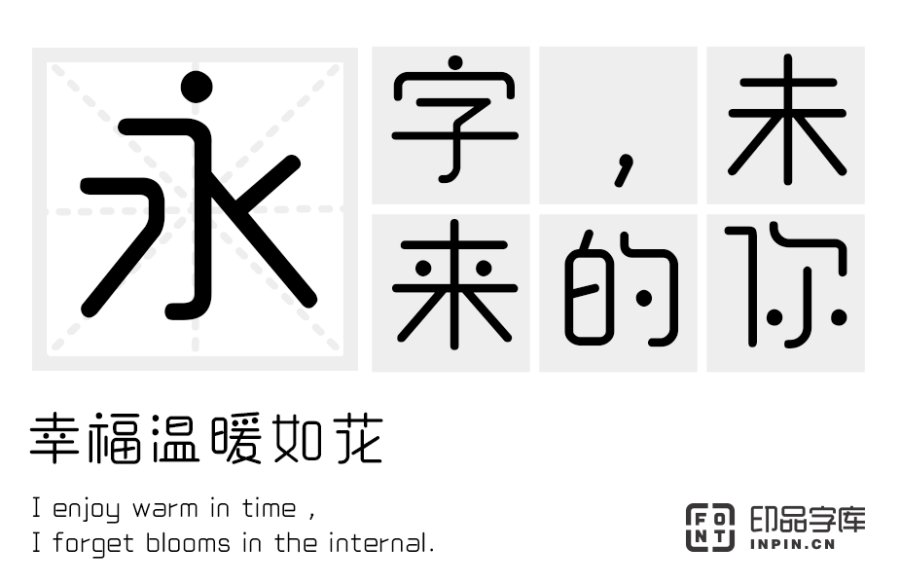
许多在线艺术字体的左边是英文,右边是中文,中英文之间形成一个非常默契的关联,无论是在阅读的时候还是在理解时,整个顺承关系比较自然,英文突出了图形,而中文进行了细微的设计可使前后形成一种呼应关系,在图形里它把这个品牌的属性寓意、意义等内容表现在内,充分利用艺术字笔画中间的强调关系,把字非常融洽非常精确的结合,让艺术字有笔画的共用,充分挖掘艺术字内部的关系和条件,利用了笔画环境让艺术字形成默契、强调的感觉。艺术字除去宣传的功用之外,还有一点就是它形成一个价值符号,这个视觉符号是独一无二的。